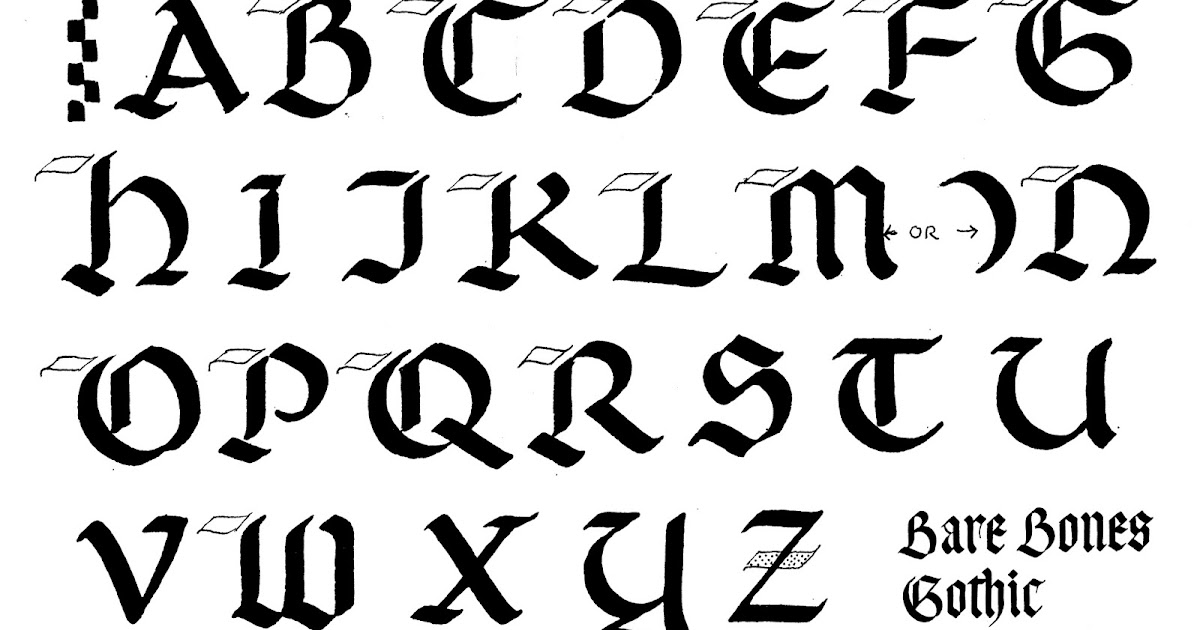
Если вы решили сделать тату с надписью, вам стоит разобраться во всех нюансах данного типа нательных рисунков. Сегодня существует масса разнообразных стилей тату, что позволяет каждому найти свой неповторимый и уникальный эскиз. При нанесении фраз для тату, афоризмов и других надписей также всегда есть пространство для креатива. В первую очередь речь идет о шрифтах для татуировок.
В последнее время шрифты тату являются определяющими, так как именно от них во многом зависит окончательный результат. Сегодня в тату-салонах Москвы можно сделать надпись, которая будет состоять из одной или нескольких букв, а возможны варианты с длинными предложениями, имеющими глубокий философский смысл. В обоих случаях можно использовать абсолютно разные шрифты для тату надписей. Иными словами, есть масса возможностей для воплощения своей фантазии и творчества.
Популярные направления шрифтов для татуировок
Обилие всевозможных стилей и направлений — это не только широкие возможности, но и определенные трудности при выборе. Среди большого количества шрифтов достаточно сложно найти свой оптимальный вариант, который поможет подчеркнуть свою индивидуальность. К наиболее востребованным направлениям шрифтов тату можно отнести:
- Каллиграфический шрифт. Данное направление имеет огромное количество вариантов, которые отличаются уникальностью почерка и стилем мастера тату.
- Готический подход. Может иметь как хорошую читабельность, так и достаточно сложную для восприятия форму. Многие известные рок-коллективы используют для своих логотипов именно этот стиль.
- Стиль граффити.
Главной особенностью является сочетание шрифтов тату и иллюстраций в одном целом. Это популярное уличное искусство все чаще используется в качестве шрифтов для тату. - Надписи с национальной спецификой. Разнообразные шрифты, присущие Азиатскому региону, Арабским странам или славянским народам, могут отличаться как особенностями письменности, так и стилистическими нюансами.
- Стилистика старой печатной машинки. В последнее время модными стали надписи, которые нанесены с эффектом старой печатной машинки, которая имеет определенные недостатки, поэтому некоторые буквы имеют визуальные дефекты. Такой подход позволяет получить уникальный результат.
К вопросу выбора стоит подойти максимально ответственно — надпись должна идеально смотреться на теле, выглядеть актуально и привлекать взгляды окружающих.
Каждый тату шрифт, представленный в нашем каталоге, обладает уникальной формой, размером, толщиной линий, расстоянием между буквами, наклоном и так далее. Потратьте несколько минут и найдите то, что позволит Вашей надписи смотреться безупречно!